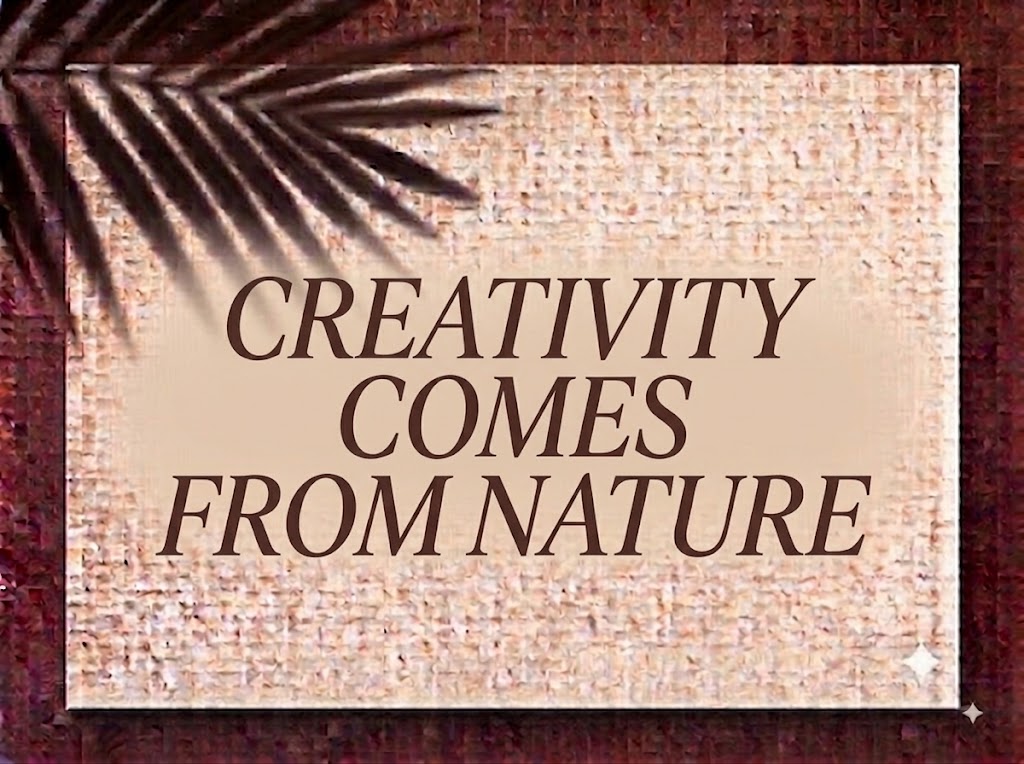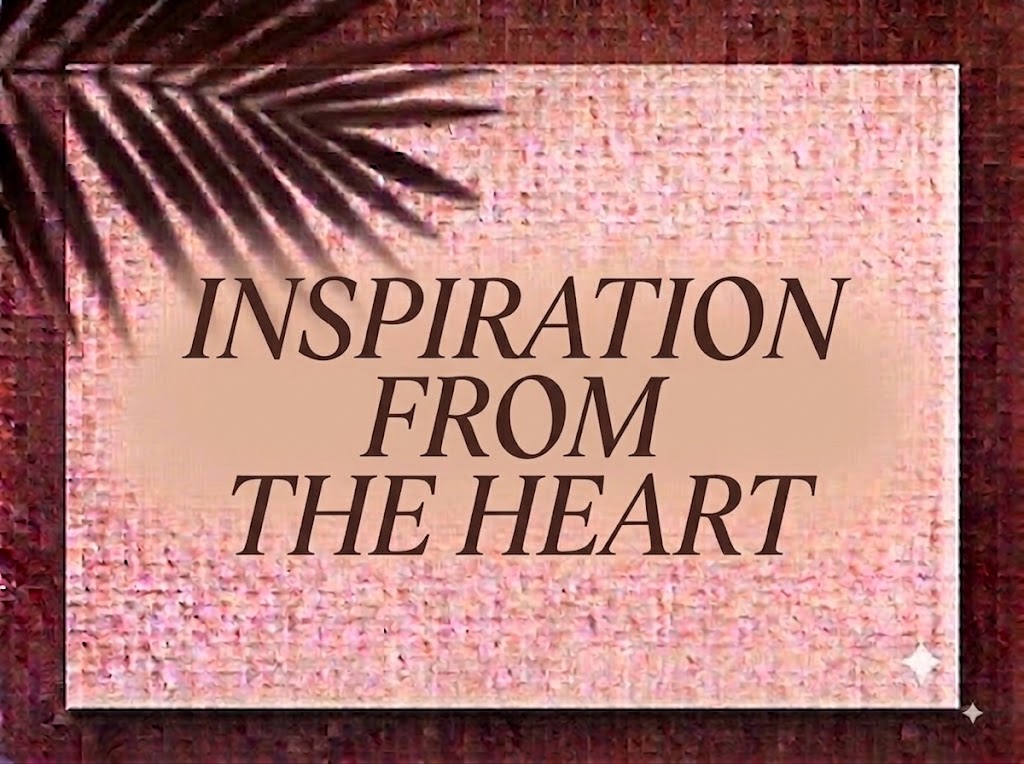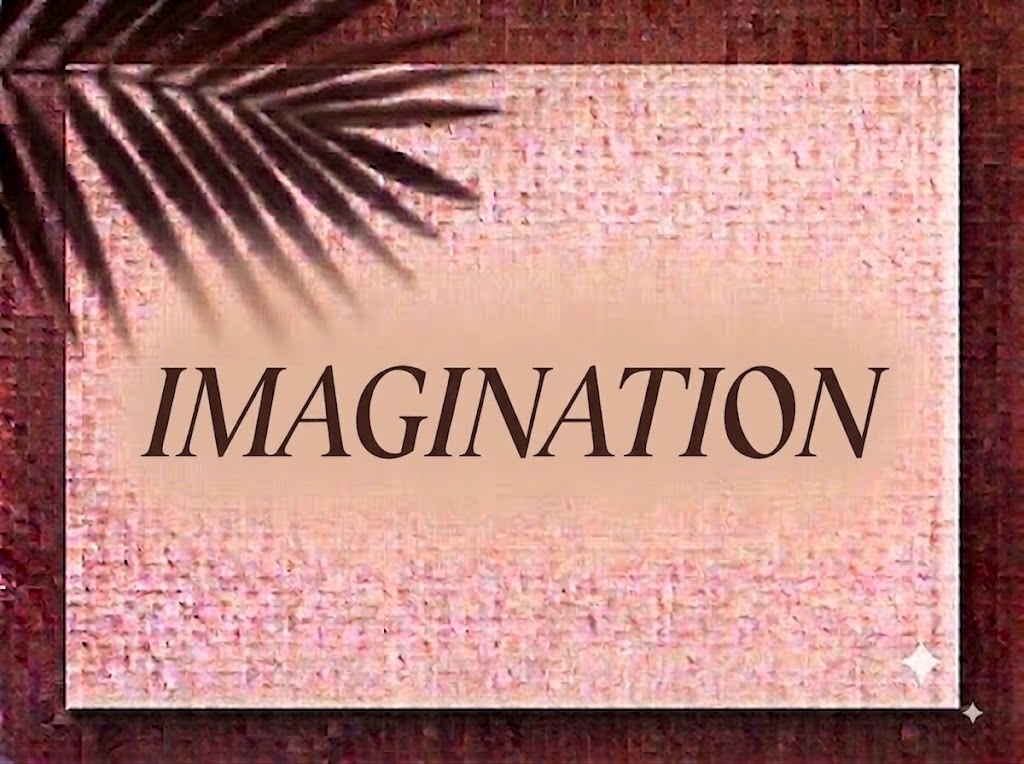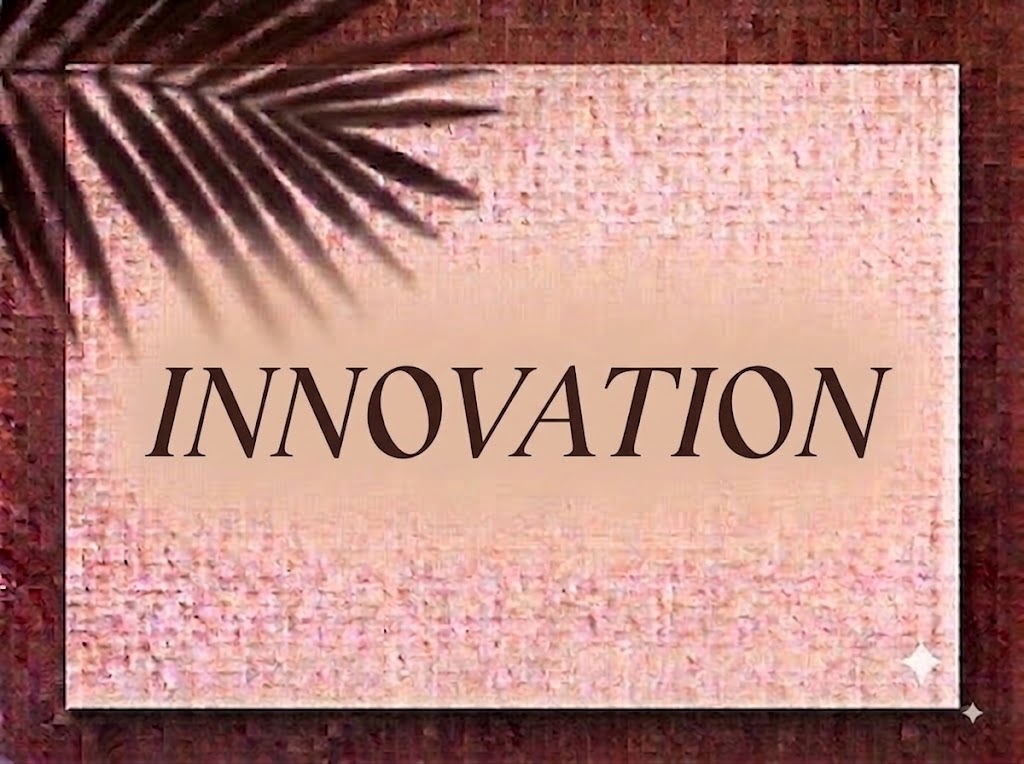
1FTV NOVE
Trong thế giới thiết kế đồ họa hiện đại, việc sở hữu một bộ phông chữ hiển thị (display font) mang nét uốn lượn mềm mại kết hợp phong cách Art Nouveau hay Retro Groovy luôn là điểm cộng lớn. Những đường nét vừa có độ cong uyển chuyển, vừa giữ được cấu trúc chắc chắn sẽ giúp dòng tiêu đề của bạn bừng sáng, gây ấn tượng thị giác mạnh mẽ ngay từ ánh nhìn đầu tiên.
Nếu bạn đang tìm kiếm một phông chữ hiển thị độc đáo, giàu tính nghệ thuật để làm logo, bìa sách, poster sự kiện, menu café hay tiêu đề video ngắn, font 1FTV NOVE chính là sự lựa chọn vô cùng tuyệt vời.
Giới thiệu về font 1FTV NOVE
Font 1FTV NOVE là bộ chữ hiển thị trang trí (decorative display font) sở hữu phong cách sáng tạo tự do, kết hợp tinh tế giữa đường nét cổ điển và tinh thần đương đại:
Tên phông chữ: 1FTV NOVE
Được chế tác kỹ lưỡng qua các công cụ biên dịch phông chữ chuyên nghiệp, 1FTV NOVE đảm bảo độ mượt và nét chuẩn xác khi hiển thị trên mọi độ phân giải. Bạn có thể tự tin phóng lớn chữ trên Photoshop, Illustrator hay các ứng dụng dựng video mà không sợ bị vỡ nét hay dính nét.
Đặc điểm nổi bật của phong cách thiết kế NOVE
Sức hút thị giác của font 1FTV NOVE đến từ phom dáng đầy tính chuyển động và những nét biến điệu ký tự đắt giá:
Chi tiết nét uốn móc độc đáo: Điểm nhấn kịch tính nhất nằm ở các nét móc uốn nhẹ ở chữ
T,F,k,h,r,m,n… Đường cong mềm mại ở phần đầu và thân chữ tạo cảm giác vừa bay bổng như nét vẽ thủ công, vừa mang hơi hướng thẩm mỹ Châu Âu cổ điển. -
Tạo hình ký tự tròn trịa, căng đầy: Các chữ cái như
a,c,e,g,o,qsở hữu cấu trúc hình khối bo tròn đặn, tạo sự cân bằng và nhịp điệu thị giác rất dễ chịu khi xếp thành câu tiêu đề. -
Đồng bộ trọn bộ chữ hoa, chữ thường và chữ số: Bộ ký tự chữ hoa kiên cố kết hợp mượt mà cùng dàn chữ thường mềm mại và dãy số 0-9 dáng đứng độc đáo, giúp designer dễ dàng phân tầng nội dung trong cùng một bản vẽ.
Để phông chữ vận hành mượt mà trên cả hệ điều hành Windows lẫn macOS, phiên bản này đã được xử lý kỹ lưỡng về mặt thông số nội tại:
Khoảng cách giữa các chữ (kerning) và độ giãn dòng được tính toán chuẩn xác, giúp các đường uốn khi đứng cạnh nhau không bị dính nét hay rối mắt.
Tích hợp trọn vẹn bộ chữ cái hoa – thường, dãy chữ số 0-9 phom dáng nghệ thuật cùng hệ thống ký tự đặc biệt, dấu câu thông dụng.
Bản Việt hóa chuẩn chỉnh giúp bạn hoàn toàn yên tâm thiết kế các văn bản tiếng Việt có dấu phức tạp mà không gặp lỗi nhảy font hay mất ký tự.
Hình ảnh demo thực tế của font 1FTV NOVE
Khả năng hiển thị của phông chữ này được tối ưu rất tốt trên nhiều tỷ lệ kích thước khác nhau:
Kích thước nhỏ (12pt – 24pt): Cấu trúc nét rành mạch giúp các khối chữ thường và dãy số vẫn hiển thị rõ ràng trên các giao diện màn hình di động.
Kích thước lớn (36pt – 72pt): Đây là đất diễn ấn tượng nhất để 1FTV NOVE phô diễn toàn bộ vẻ uyển chuyển, nghệ thuật và nét móc uốn phá cách, tạo tác động thị giác cực kỳ thu hút cho các dòng headline chính.
Ứng dụng trong thiết kế đồ họa và làm video
Sở hữu nét cá tính nghệ thuật và bay bổng, font 1FTV NOVE mở ra không gian ứng dụng vô cùng phong phú:
Video ngắn (TikTok, Reels, Shorts): Dáng chữ uốn lượn rất thu hút trên khung hình đứng tỷ lệ 9:16. Cực kỳ ăn nhập với các video vlog nghệ thuật, podcast tâm sự, nhạc Indie, Acoustic, DIY handmade hay clip thời trang vintage.
Ảnh thu nhỏ YouTube (Thumbnail): Lựa chọn tuyệt vời cho các kênh làm nội dung về âm nhạc, review phim, sách, đời sống hay nghệ thuật sáng tạo nhờ giao diện độc lạ, gây tò mò.
Thiết kế Poster, Bìa sách & Triển lãm: Hoàn hảo cho các poster sự kiện âm nhạc, bìa tiểu thuyết, triển lãm mỹ thuật hay poster phim nghệ thuật.
Nhận diện thương hiệu & Bao bì: Thích hợp làm logo dạng chữ cho quán café, tiệm bakery, cửa hàng đồ gốm/decor, nhãn mác nước hoa, mỹ phẩm hữu cơ hay các thương hiệu thời trang cá tính.